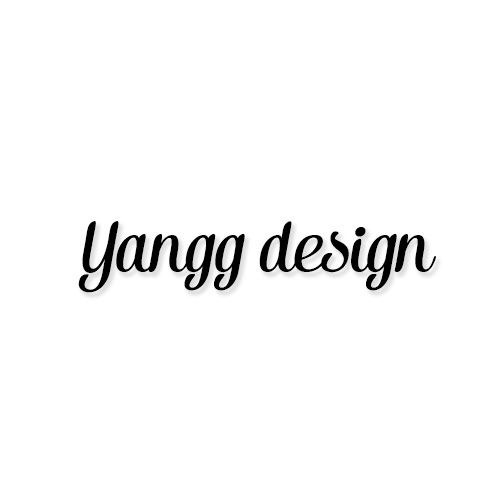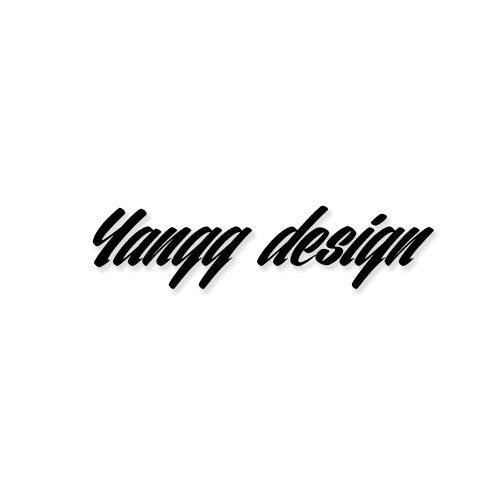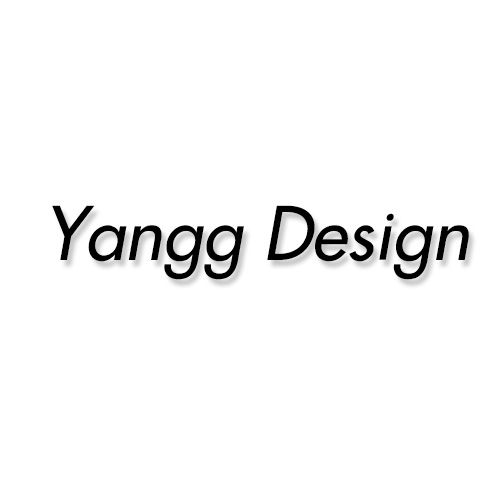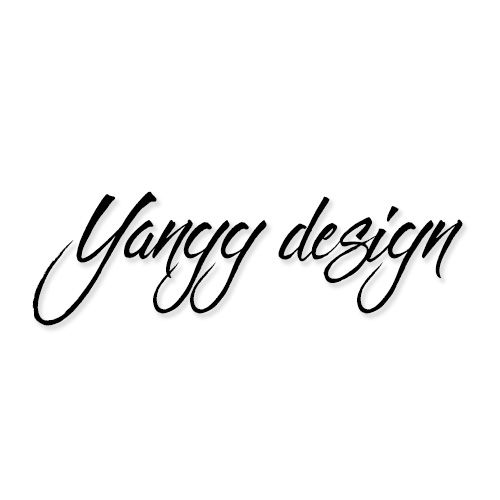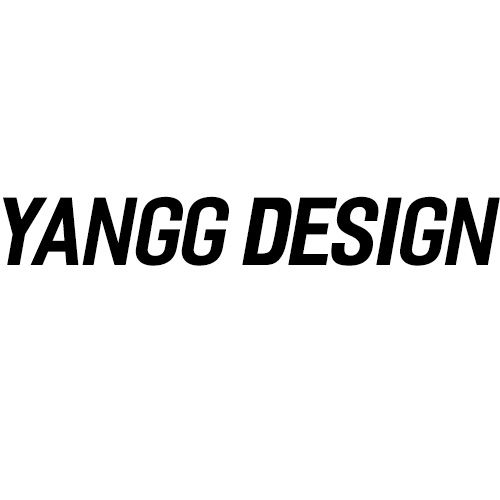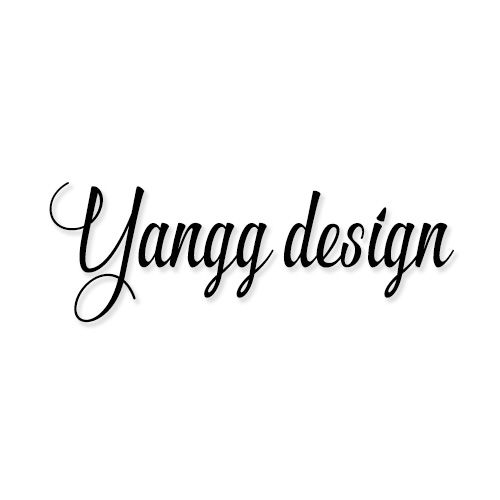
Tớ thấy có nhiều bạn sử dụng font lỗi hoặc là một font mà dùng đi dùng lại.
Nên hôm nay tớ chia sẻ cho các cậu những font Việt Hóa đẹp.
Tớ sẽ giới thiệu một số font đẹp mà ít người biết đến để sử dụng, còn những font quá phổ biến như FS Playlist, FS Bandung, FS The Southamton. . . thì tớ không giới thiệu lại nữa.
- Dưới đây là một số tên font và hình ảnh font.
1. Font "SVN Alek": Font này dễ nhìn dễ đọc (Font mềm)
2. Font "SVN Fresh Script" : Font này hơi loạn dành cho des cute size là đẹp (Font mềm)
3. Font "UVF ventography": Font này khá giống FS The Southamton (Font mềm)
4. Font "VL Wolfsbane": Font này rất hợp des quotes text chính nhé (Font mềm)
5. Font "iCielFesterSemiCondensed-Bold": Wow! Tên khó nhớ lắm, tớ phải viết mãi mới được đấy, nhìn vậy thôi chứ đẹp lắm (Font cứng)
6. Font "Fujyama": Font này cũng hợp với quotes text phụ, thay thế cho Times New Roman (Font cứng)